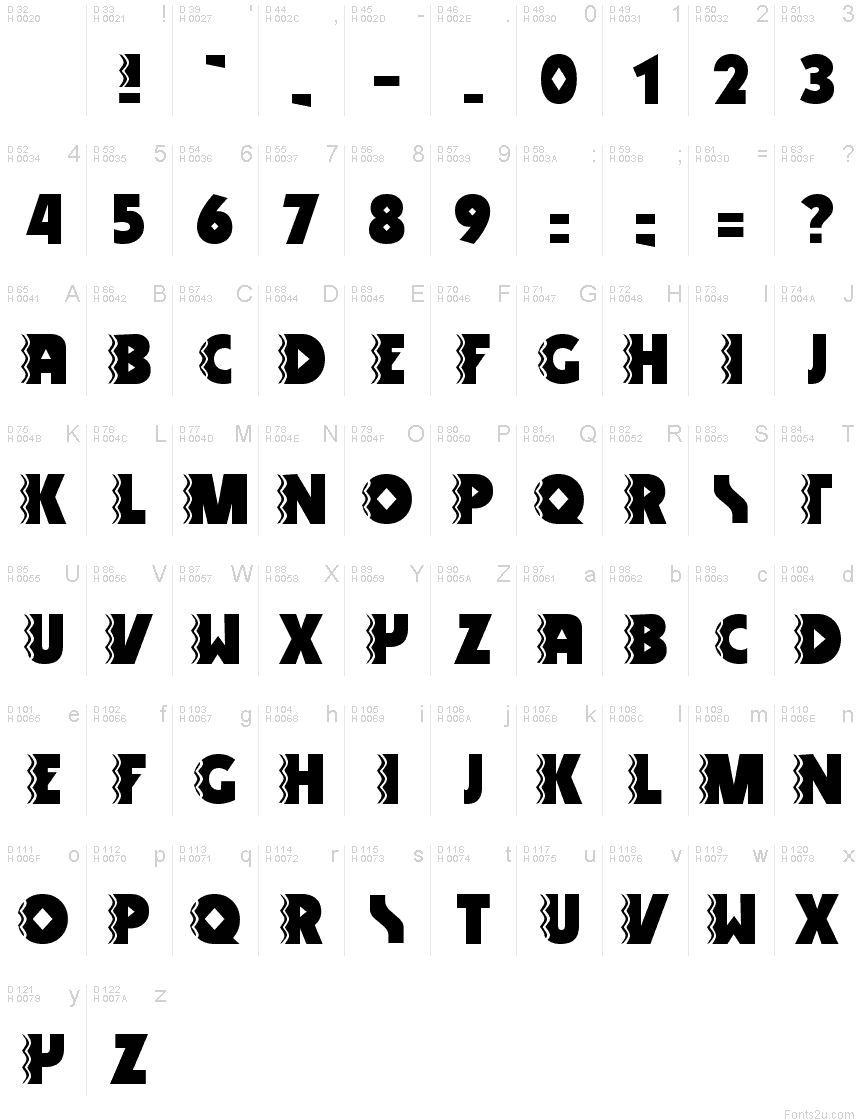
Snake Venom od Levi to darmowy krój typu display w stylu groovy, z psychodelicznym pulsem końca lat 60. i sprytnym nawiązaniem do skóry węża. Wielkie litery są duże, masywne i kanciaste, ale każda z nich jest przecięta falistymi kanałami, przez co cały font wydaje się drgać w miejscu.
Świetnie sprawdza się na plakatach, okładkach płyt, festiwalowych ulotkach, szkicach logo i odważnych projektach opakowań, gdzie liczy się charakter, a nie subtelność. Jako darmowy font najlepiej sprawdza się w krótkich nagłówkach, tytułach czy monogramach, ponieważ te wijące się wycięcia nadają nawet prostym słowom ruchomą, hipnotyczną teksturę.